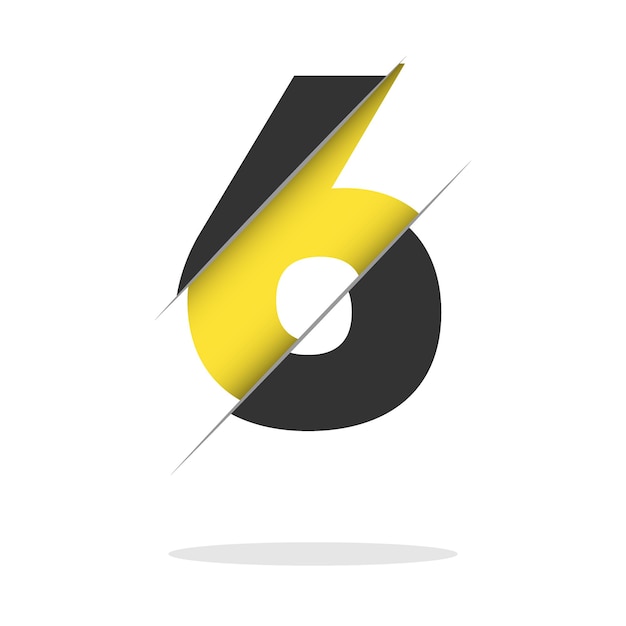
Numer Cięcia Papieru Sześć Liter Realistyczny Efekt Wielowarstwowego Wycinania Papieru 3d Na Białym Tle Rysunek Czcionki Litery Alfabetu Element Dekoracji Na Urodziny Lub Projekt Powitania Weselnego